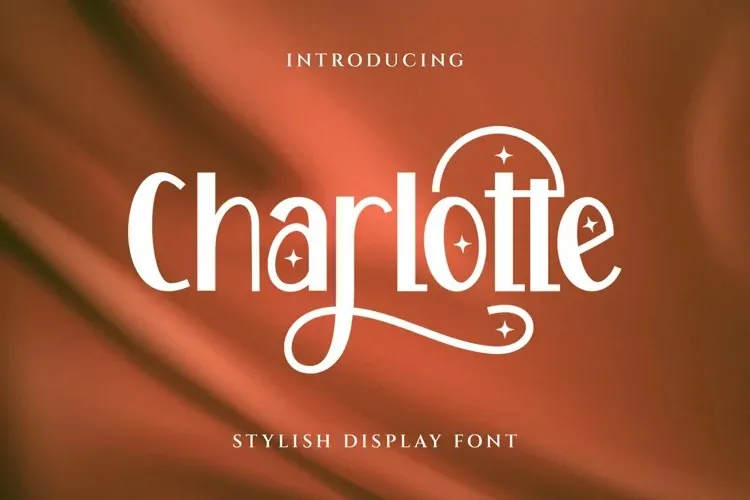
A Font Charlotte é uma elegante escolha para quem busca uma tipografia forte e limpa, perfeita para uso em diversos ambientes. Criada pela Graphicxell, essa fonte de tipo display oferece um design sólido e clean, ideal para criações como moda, marcas, convites, hotéis, beleza, produtos, citações, designs de produtos, artesãos, etiquetas, fotografia e água-marinhas. É uma ótima opção para designers que precisam de uma fonte forte e limpa para seus projetos em Adobe InDesign, Adobe Illustrator CS, Photoshop CC ou Corel Draw. Sua versatilidade faz dela um recurso valioso no seu arsenal gráfico.